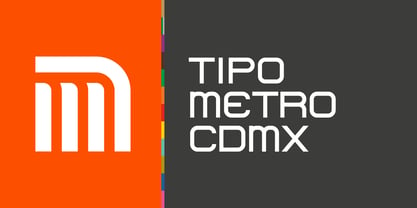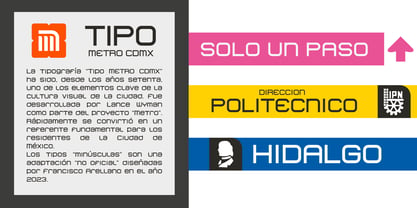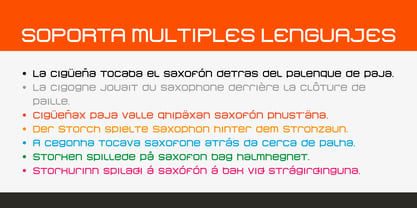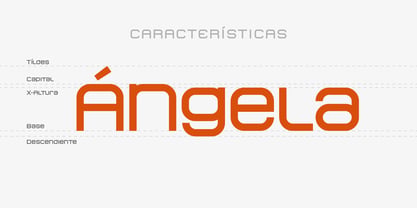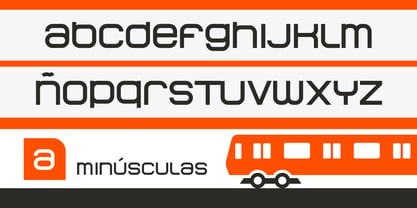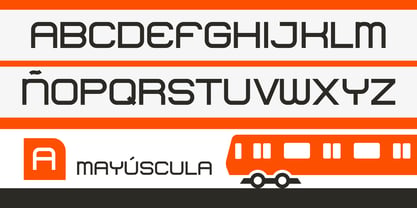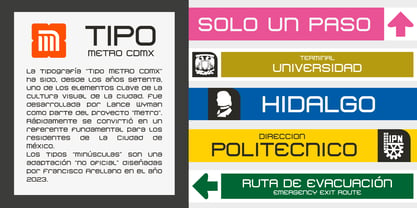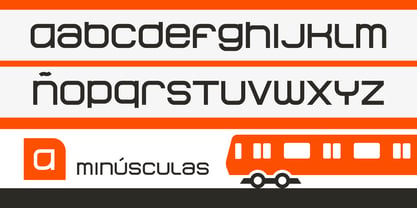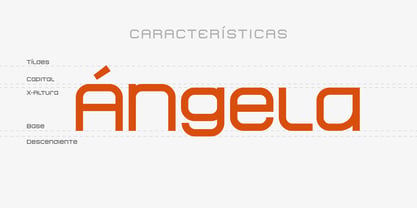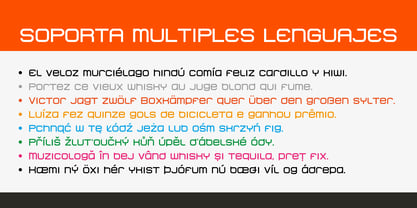
Tipo Metro CDMX
The Tipo Metro CDMX Font Family was designed by Francisco Arellano and published by Ixipcalli. Tipo Metro CDMX contains 6 styles and family package options. More about this family
La tipografía “Tipo Metro CDMX” fue desarrollada por Lance Wyman como parte del proyecto “Metro” desde los años setenta, y es uno de los elementos clave de la cultura visual del transporte del Sistema de Transporte Colectivo Metro (STC Metro). Este estilo se ha convertido en el icónico fundamental del trasporte público para los residentes de la Ciudad de México.
En esta edición, los tipos minúsculas son una adaptación “no oficial” para el Tipo Metro CDMX, enriqueciendo la tipografía a un estilo visual de altas y bajas, por lo que se prescinde del diseño base como trabajo propio para enfatizar los tipos minúsculas exclusivamente, además de que se han añadido algunos caracteres de acentuación extendiendo su uso a otros lenguajes. Los tipos son una nueva propuesta por Ixipcalli en el año 2023.
El 2 de septiembre de 2025 se ha realizado una nueva actualización, ajustando márgenes de dos caracteres erróneos y añadido las variantes ligera, negrita e itálicas.
The “Tipo Metro CDMX” typeface was developed by Lance Wyman as part of the “Metro” project since the 1970s, and is one of the key elements of the visual culture of transportation of the Metro Collective Transportation System (STC Metro). This style has become the iconic fundamental of public transportation for the residents of Mexico City.
In this edition, the lowercase types are an “unofficial” adaptation for the Tipo Metro CDMX, enriching the typography with a visual style of highs and lows, so the base design is dispensed with as my own work to emphasize the lowercase types exclusively, In addition, some accentuation characters have been added, extending their use to other languages. The types are a new proposal by Ixipcalli in the year 2023.
On September 2, 2025, a new update was released, adjusting margins for two erroneous characters and adding light, bold, and italic variants.